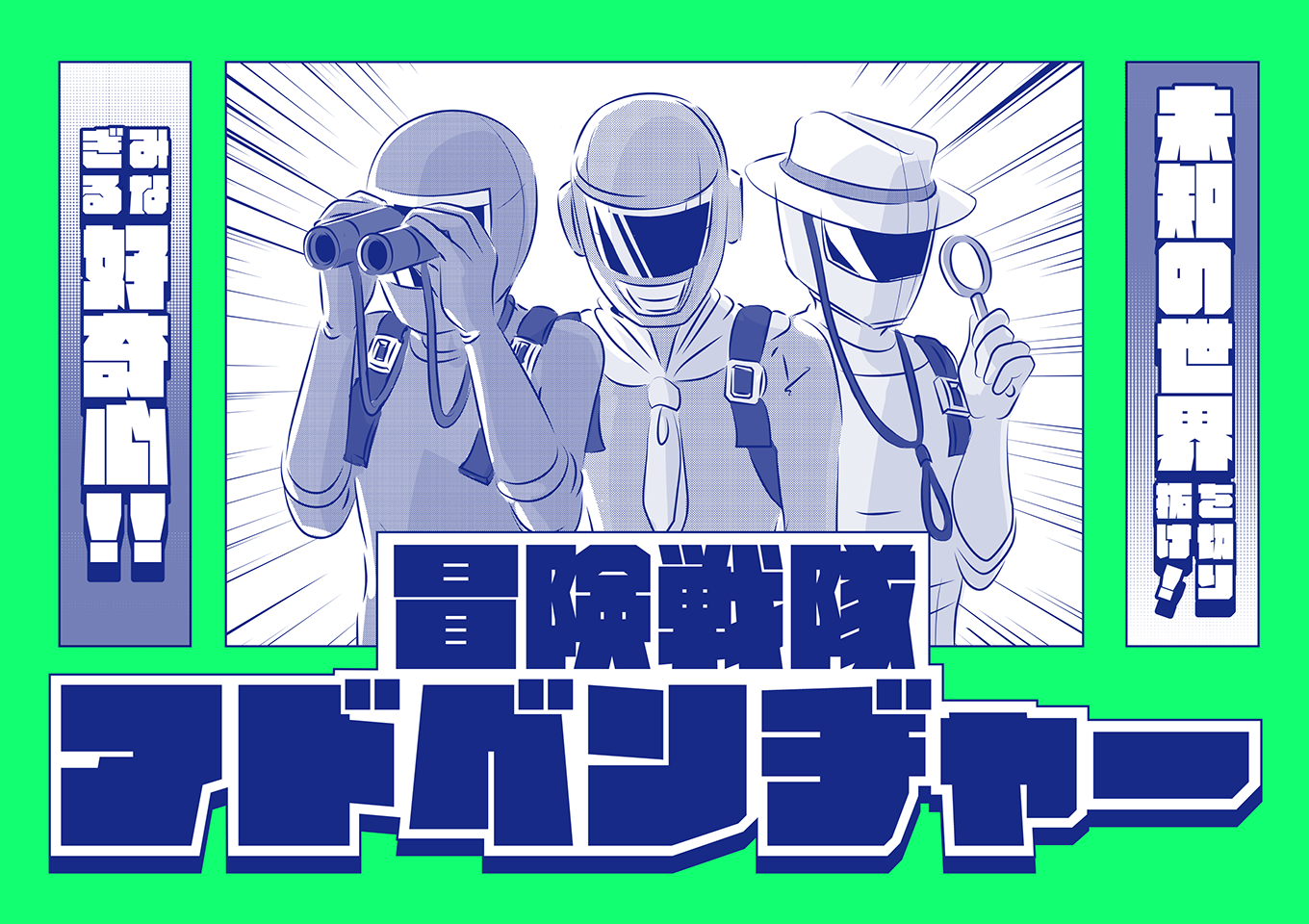
「ボルクロイド」は、見出し利用に特化した硬質で力強いイメージのデザイン書体です。直線のみで構成された骨格に限界まで太くしたエレメントを組み合わせ、パワフルでエッジの効いたロゴタイプのような作風に仕上げています。字面も大きく図形的なインパクトがあり、漫画やアニメのタイトルやポスターの見出しなど大きく使うことで活躍する書体です。